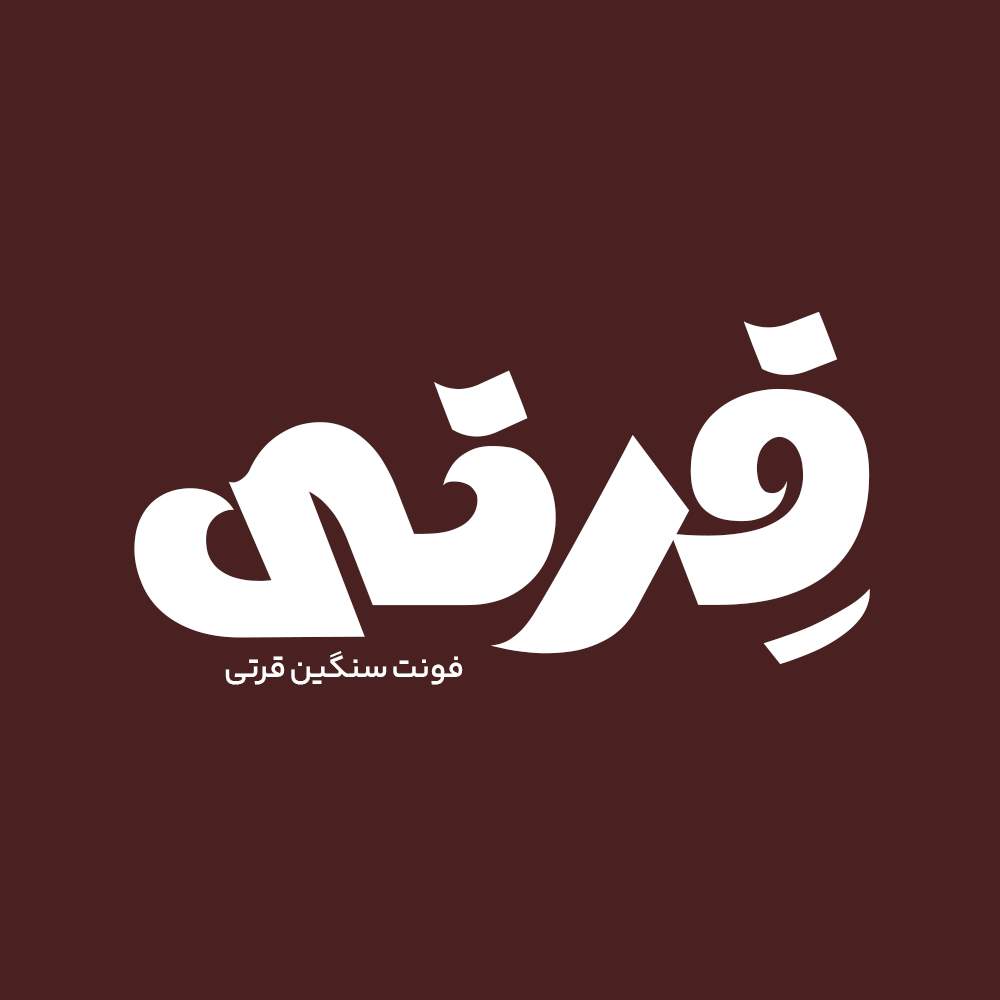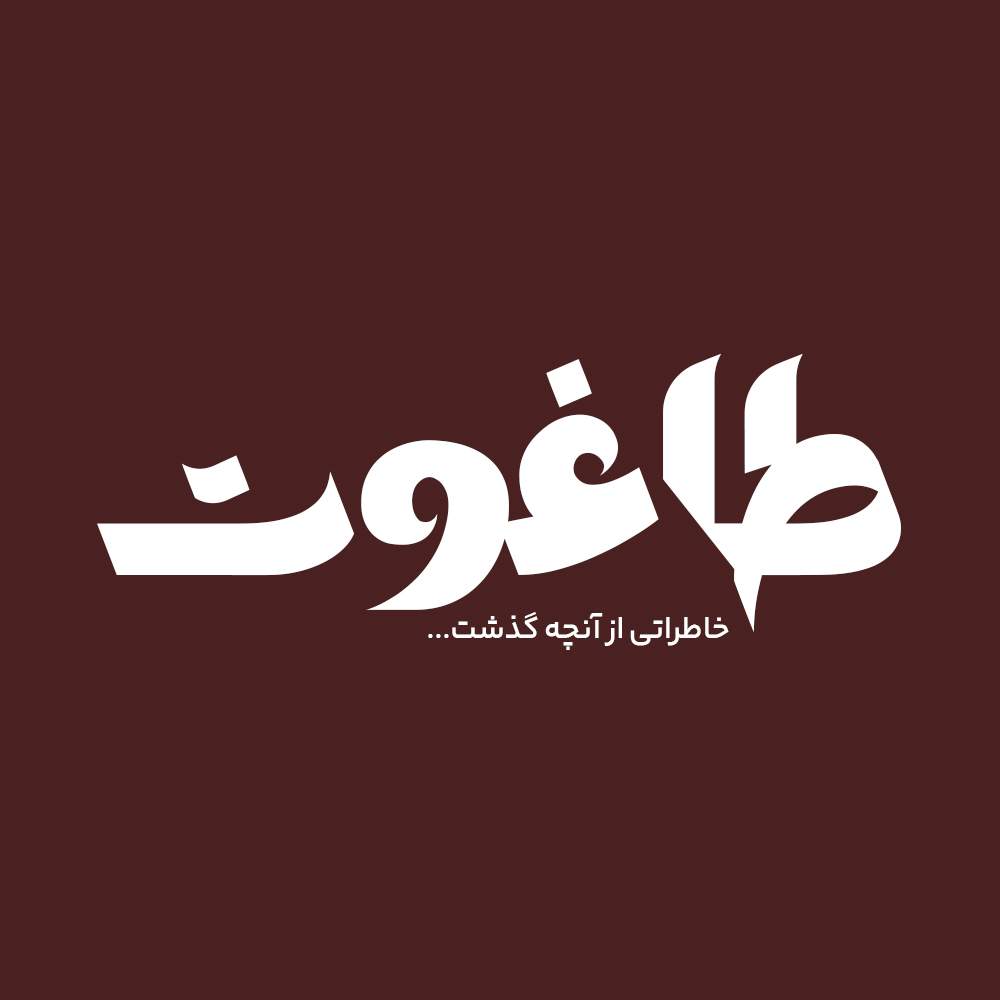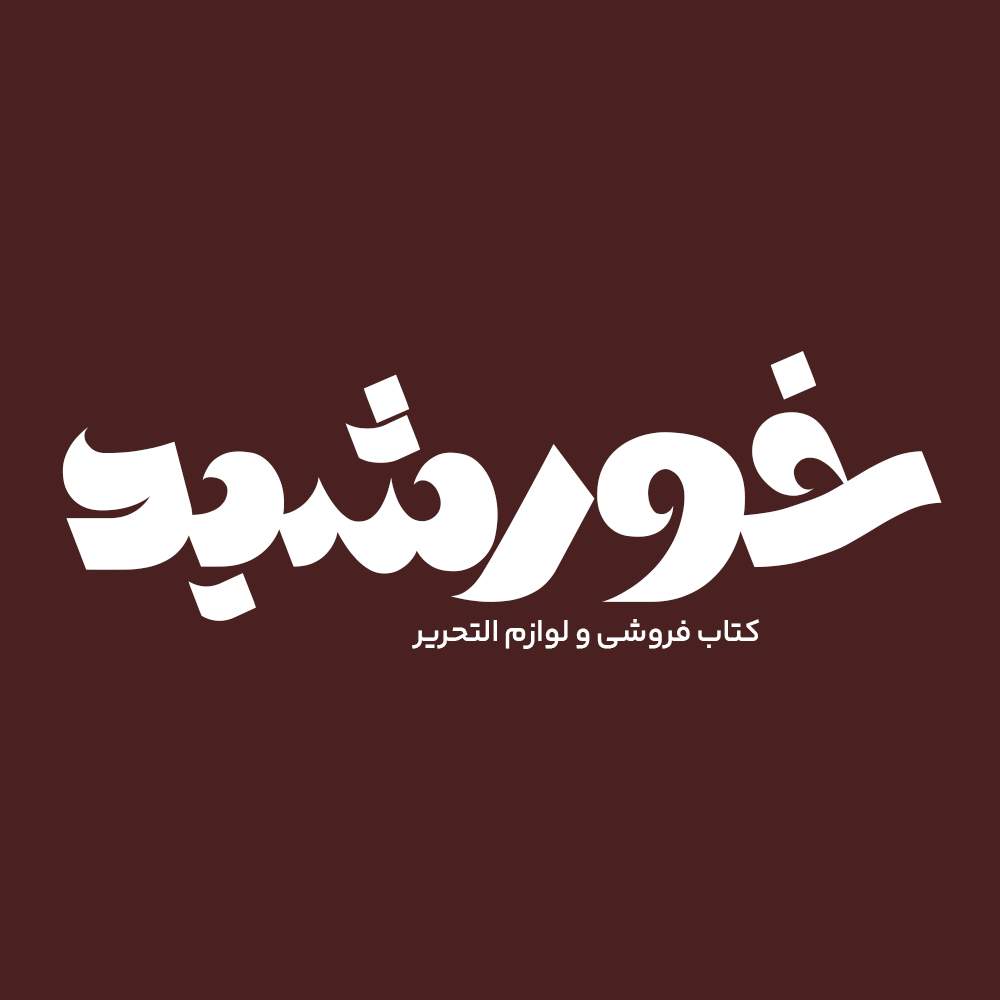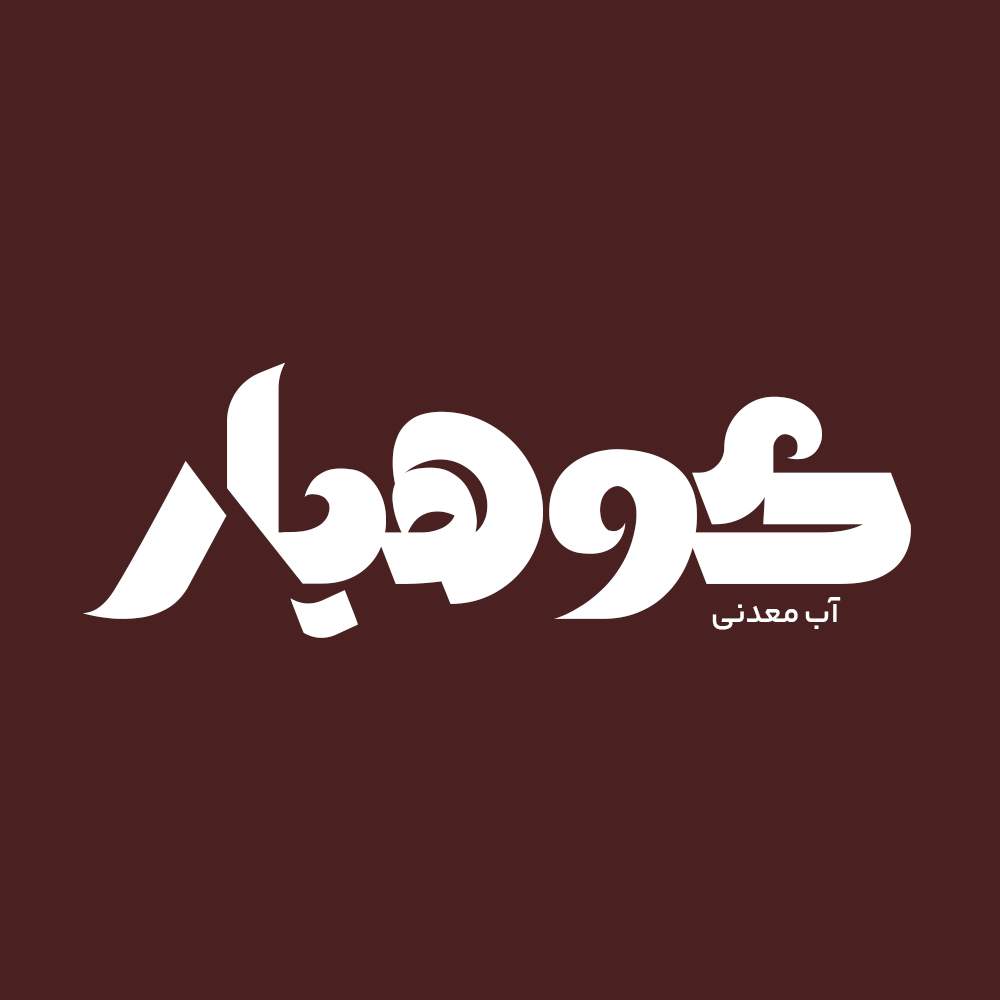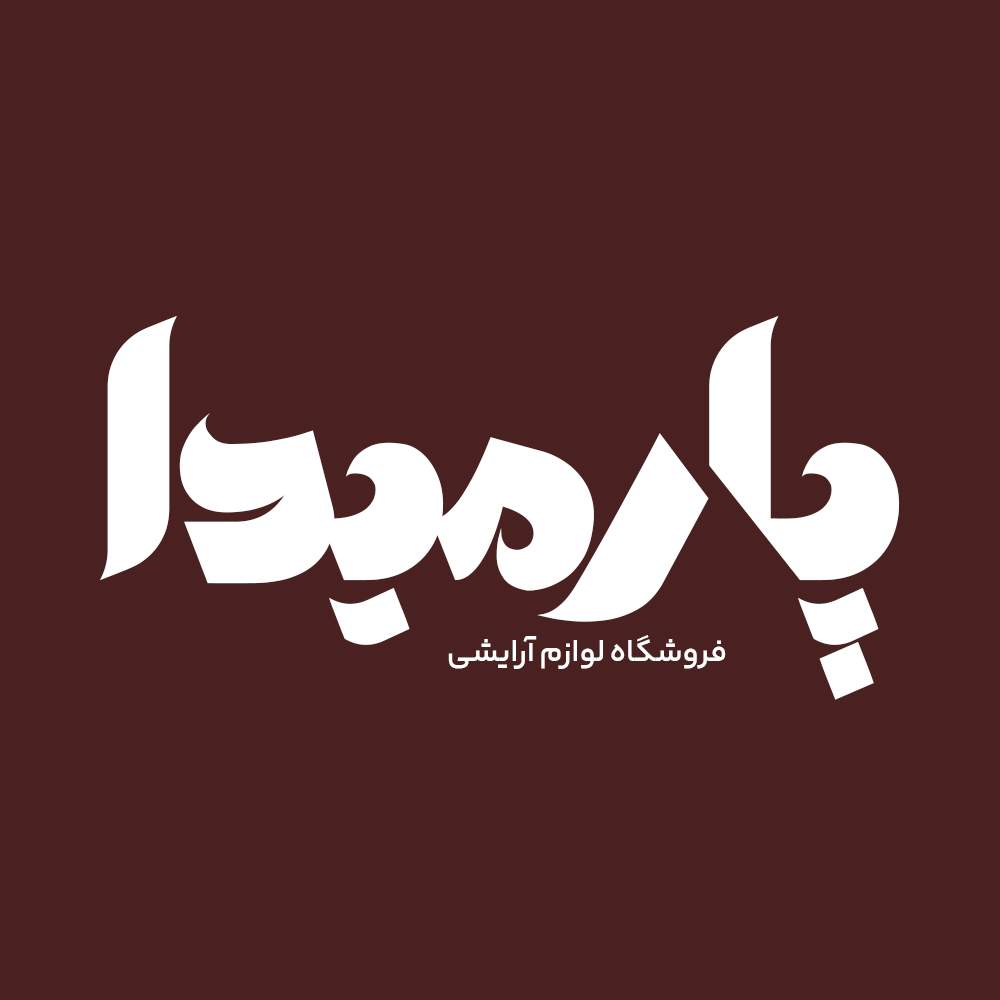
فونت فارسی قرتی Gherti Font
فونت فارسی قرتی یک فونت متفاوت و زیبای فارسی می باشد که در وزن بولد طراحی شده است، فونت قرتی یک فونت بولد فارسی می باشد…
فونت فارسی قرتی یک فونت متفاوت و زیبای فارسی می باشد که در وزن بولد طراحی شده است، فونت قرتی یک فونت بولد فارسی می باشد که با طراحی و سبک خاصی که دارد از سایر فونت های این سبک متفاوت می باشد، این فونت زیبا در عین سادگی که فونت های بسیار سنگین دارند یک طراحی خاص دارد که سبب متفاوت شدن و هنری تر شدن این فونت میشود. فونت قرتی مناسب انواع طراحی گرافیکی می باشد.
فونت فارسی قرتی یک فونت تک وزن با سبک نسخ و با کاربرد طراحی لوگوتایپ و طراحی های مختلف همچون کتاب و تولید محتوای متن های کوتاه و عناوین می باشد. این فونت با ساختار حروف خود مناسب استفاده در لوگوهای نوشتاری می باشد. همچنین از این فونت در طراحی تابلوهای چلنیوم هم به دلیل ساختار منحصر به فردش می توانید استفاده کنید. در ادامه برای شما نمونه تایپ های این محصول حرفه ای رو آماده کردیم که میتونید مشاهده کنید.